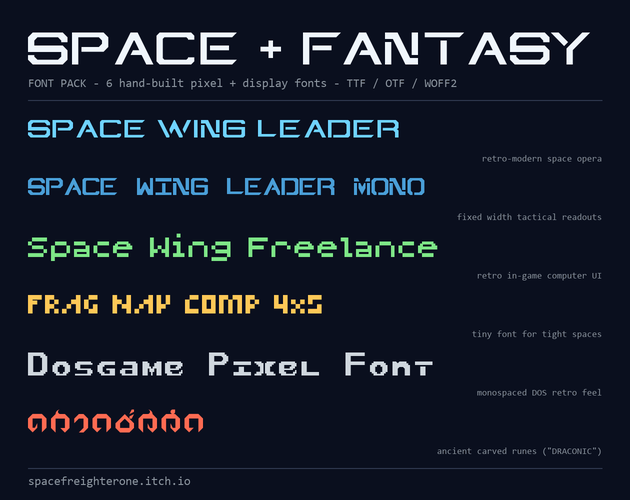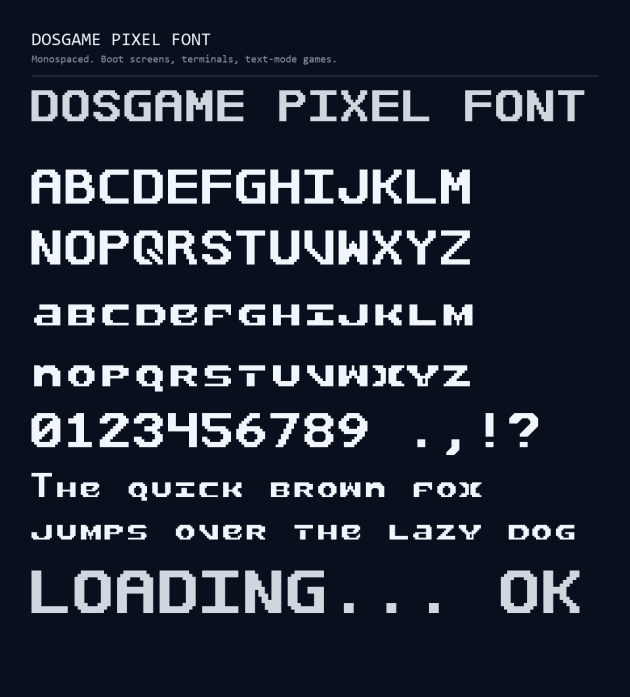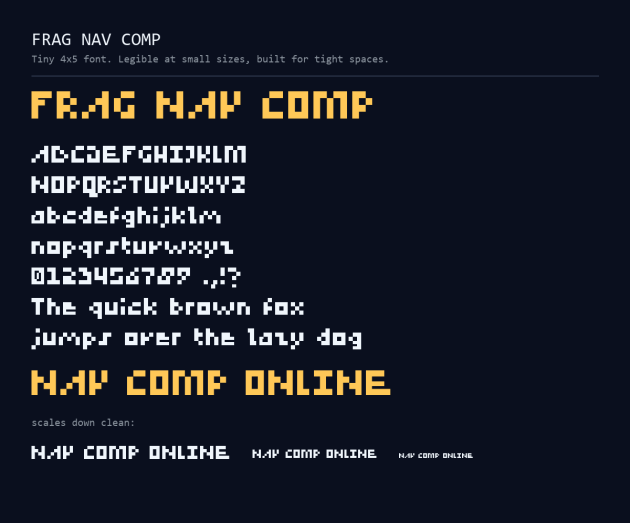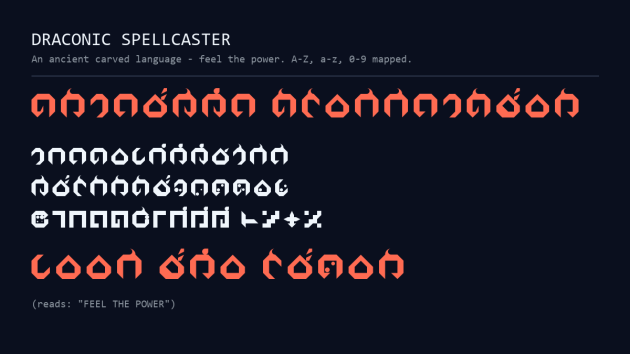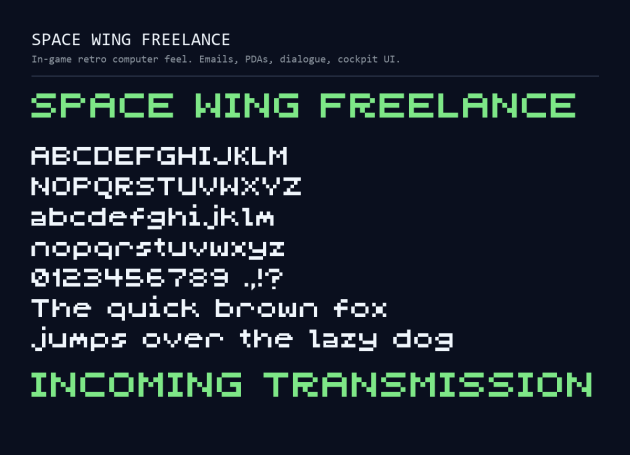
六款受经典游戏启发的复古像素字体素材,全部使用 FontStruct 手工打造。驾驶舱显示、DOS 终端,以及神秘的魔法——尽在一个字体包中。每款字体都包含 TTF、OTF 和 WOFF2文件。
DOSGAME 像素字体
等宽字体。非常适合营造复古氛围——开机画面、终端和文字模式游戏。
SPACE WING LEADER字体
复古现代太空歌剧风格。标题画面、HUD界面和任务简报均采用大型镂空字体。
SPACE WING LEADER MONOSPACE字体
采用固定宽度的太空歌剧风格——适用于需要列对齐的战术读数和终端。
SPACE WING FREELANCE字体
游戏内复古电脑风格。非常适合用于电子邮件、PDA、对话框和驾驶舱用户界面。
SPACE WING FREELANCE – FRAG NAV COMP字体
当屏幕空间有限时,这款 4×5 的小字体就能派上用场——小尺寸下清晰易读,专为狭小空间而设计。
DRACONIC SPELLCASTER字体
一种古老的雕刻语言——感受它的力量。输入英文,每个字母都会变成一个龙符文。AZ、az 和 0-9 都已映射,聪明的玩家可以真正破译它。